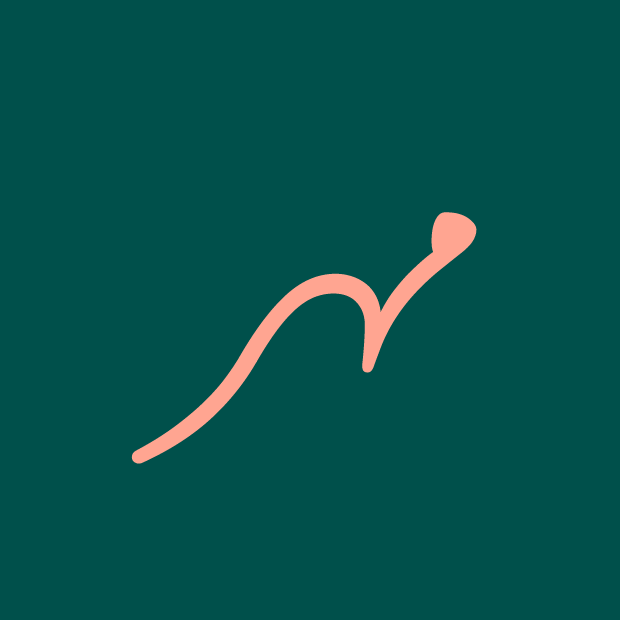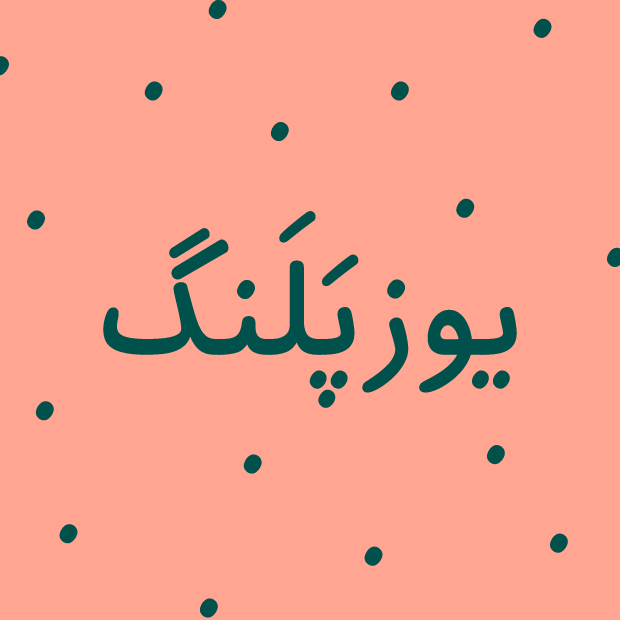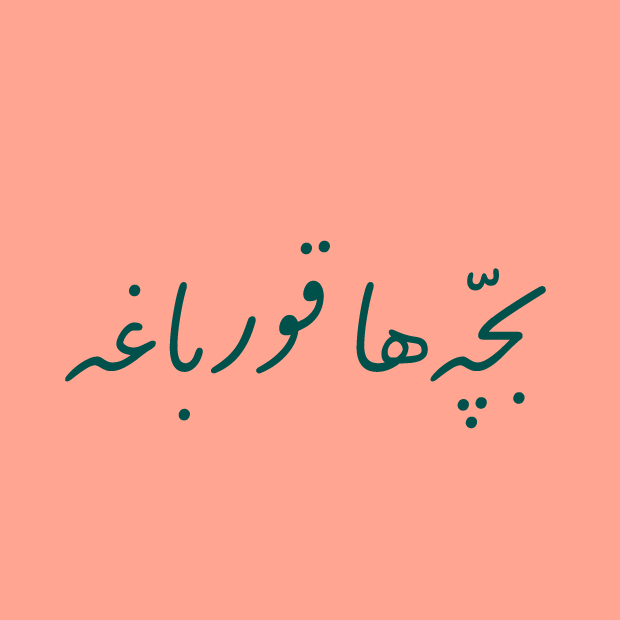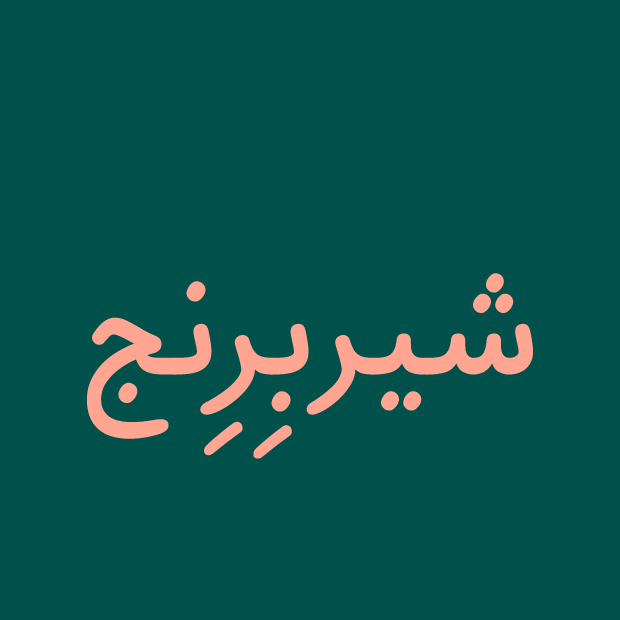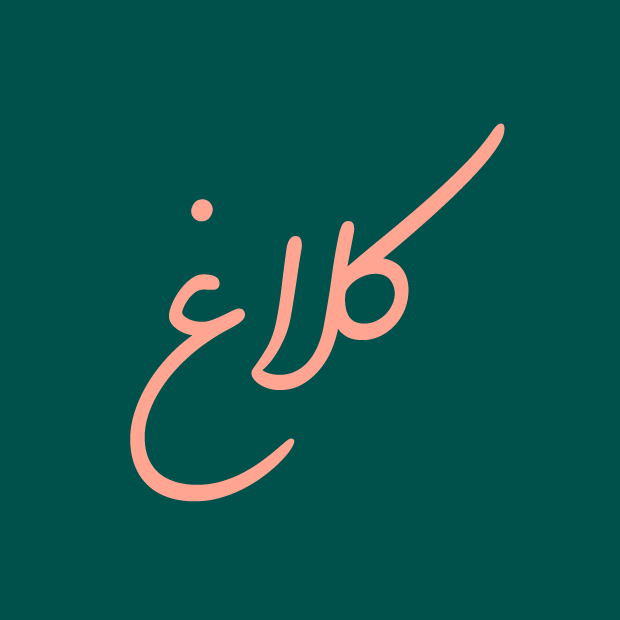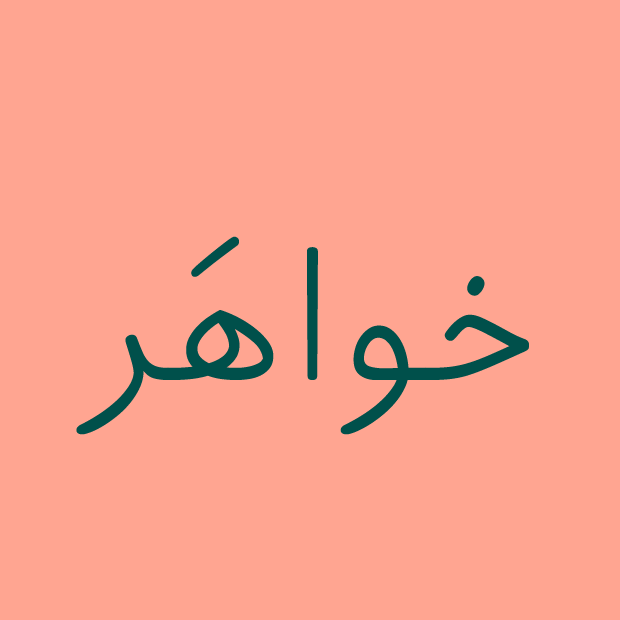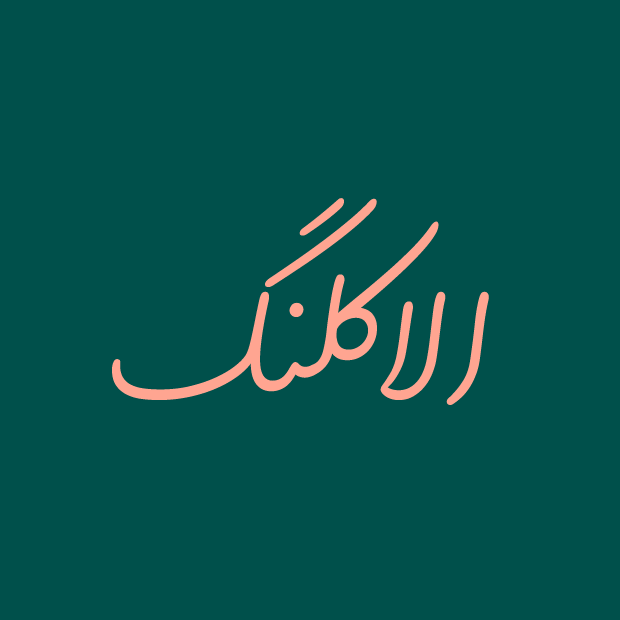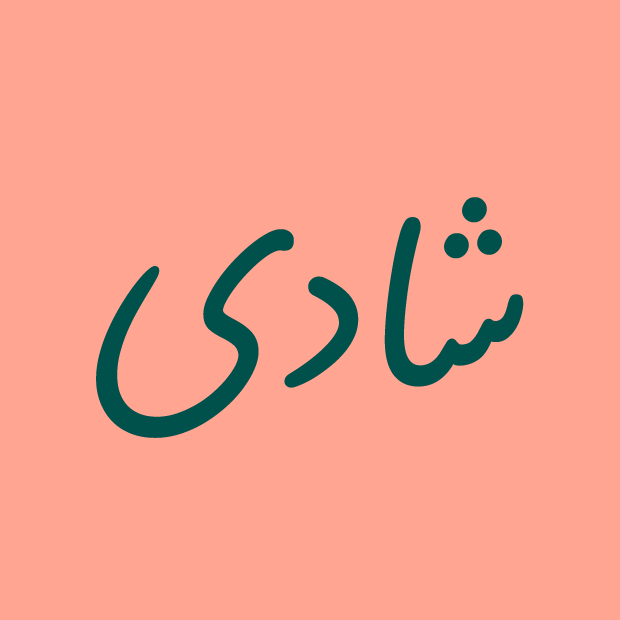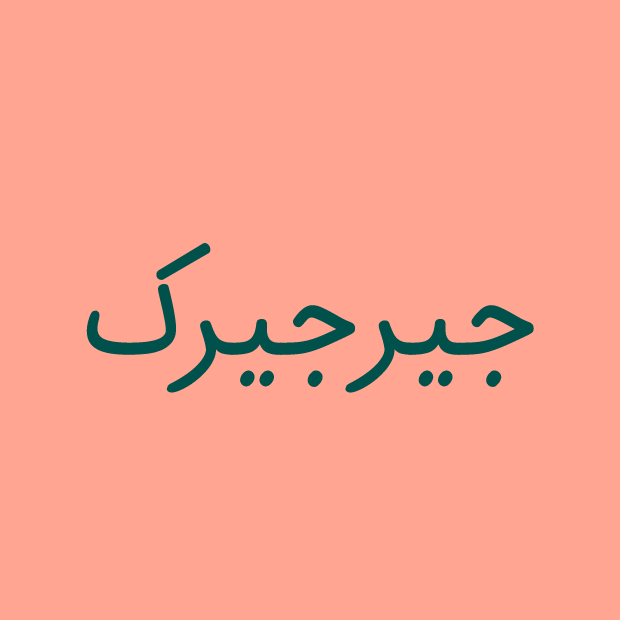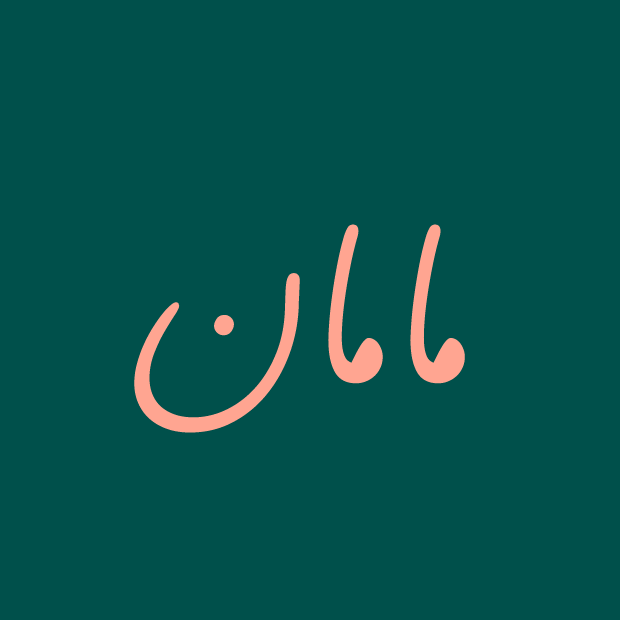
قلم دبستان font Dabestan
قلم دبستان
کاری از امید امامیان و رضا بختیاری فرد
درباره قلم دبستان
دبستان خانواده‌ی قلمی برای دانش‌آموزان پایه اول تا ششم دبستان است؛ یعنی کودکان ۷ تا ۱۲ ساله. در مورد سطح سواد، هم با دانش‌آموزانی سروکار داریم که در ابتدای راه بوده و لوح ذهنشان خالی از هرگونه پیش‌زمینه‌ی نوشتاری است، هم دانش‌آموزانی که در پایه ششم در حال رفتن به مقطع بالاترند. ضمن این‌که آموزگاران نیز بخش مهمی از روند آموزش به حساب می‌آیند؛ پس می‌بایست قلمی طراحی شود که هم آموزگاران بتوانند به راحتی آموزش بدهند و هم دانش‌آموزان بتوانند به راحتی از پس خواندن نوشته‌ها و یادگیری آن‌ها برآیند.
این قلم در کنار بهبود سرعت و کیفیت یادگیری دانش‌آموزان، الگوی مناسبی برای تقلید بوده و در نهایت با کمک آموزگار، باعث تربیت افرادی خوش‌خط می‌شود. خانواده‌ی قلمی که نه تنها در حروف؛ بلکه در اعداد، علائم و حرکت‌گذاری‌ها کاملاً کاربردی بوده و مناسب استفاده در همه‌ی درس‌های ابتدایی از جمله: فارسی، ریاضی و قرآن باشد.
قلم دبستان دارای دو پایه‌ی «سوادآموز» و «پیشرفته» است. اسکلت حروف پایه‌ها مرتبط بوده و از نظر فرم رو به تکامل می‌روند. پایه‌ی «سوادآموز» درپایه‌ی اول و دوم دبستان و پایه‌ی «پیشرفته» درپایه‌ی دوم تا ششم کاربردی است؛ هر پایه هم دارای سه وزن «رگولار»، «سمی‌بولد» و «بولد» است.
در آغاز طراحی، درباره‌ی فضاهای آموزشی و تحقیقات صورت‌گرفته در داخل و خارج از کشور تحقیق کردیم. قلم‌های پرکاربرد سوادآموزی فارسی و انگلیسی هم با دقت بررسی نموده و همین‌طور با افراد باتجربه که قبلاً در این زمینه کار کرده بودند یا در محیط آموزشی با دانش‌آموزان سروکار داشتندجلساتی برگزار کردیم. در نتیجه:
خوانایی، تقلیدپذیری، سادگی، کارایی، مهربانی و صمیمیت شاخصه‌های اصلی این قلم هستند. [ادامه مطلب...]
امید امامیان
متولد ۱۳۶۸، کارشناس گرافیک و طراح تایپ ایرانی است، از سال ۱۳۹۱ فعالیت حرفه‌ای خود را در حوزه طراحی تایپ‌فیس آغاز کرده است. امید تاکنون فونت‌های متعددی را به صورت مستقل و یا در همکاری با طراحان مختلف مانند: رضا بختیاری‌فرد، مهدی ارشادی و کامیاب جعفری طراحی و توسعه داده است. از آثار او می‌توان به فونت‌های: جام‌جم، آرامش، واضح، دبستان، ری، ایرانسل، آریا، میکا و کمند اشاره کرد.
امید جوایز متعددی از جمله ۳ دوره نشان ممتاز تایپوگرافی TDC(۲۰۱۸ – ۲۰۱۹ و ۲۰۲۱) رتبه دوم و دیپلم افتخار گرانشان (۲۰۱۴ – ۲۰۱۷) و دیپلم افتخار سرو نقره‌ای ۱۳۹۶ را کسب کرده است.
او علاوه بر فعالیت حرفه‌ای، به عنوان مدرس در مدرسه دیزاین و ارتباطات ویژه و دانشگاه‌ سوره به تدریس طراحی تایپ مشغول است. وی همچنین کارگاه‌ها و سخنرانی‌های متعددی را در این زمینه برگزار و در نمایشگاه‌های داخلی و خارجی تایپ دیزاین شرکت داشته است.
رضا بختیاری فرد
تایپوگرافر
مدرس طراحی تایپ‌فیس و لوگوتایپ
تجربه‌های کاری
• طراحی قلم‌های ایرانسل، ابَر، پیکان، لیلا، باغ کتاب تهران و راوی
• طراحی قلم‌های مای‌بیبی، علی‌بابا، اینورس، بانک آینده، بنیاد کودک و فانوس با هم‌کاری مهدی ارشادی
• طراحی قلم‌های میکا، واضح، ری و دبستان با هم‌کاری امید امامیان
• طراحی قلم یکان بخ (بازطراحی قلم یکان) با هم‌کاری ماهان جعفرزاده
• طراحی قلم دوران، طراح: فرشته ایرانشاهی و رضا بختیاری فرد
• طراحی قلم نیان، طراح: افسانه سالک، رضا بختیاری فرد
• طراحی قلم نوین‌وب بانک اقتصاد نوین (بازطراحی و بهینه‌سازی قلم نوین)
آثار برگزیده
دریافت سه نشان تایپوگرافی ممتاز TDC (باشگاه طراحان تایپ امریکا) ۲۰۱۸ و ۲۰۲۱ و اثر منتخب هیئت داوران | جایگاه سوم مسابقه‌ی بین‌المللی قلم گرانشان ارمنستان ۲۰۲۲ | دیپلم افتخار مسابقه‌ی بین‌المللی قلم گرانشان ارمنستان ۲۰۱۷ | جایگاه اول سرو نقره‌ای ۹۲ | شایسته‌ی تقدیر در سرو نقره‌ای ۹۶ | جایزه‌ی عالی در بخش حرفه‌ای اولین دوسالانه‌ی بین‌المللی طراحی جاده ابریشم چین ۹۵ | شایسته‌ی تقدیر در نخستین سالانه‌ی طراحی کتاب ایران ۹۴.